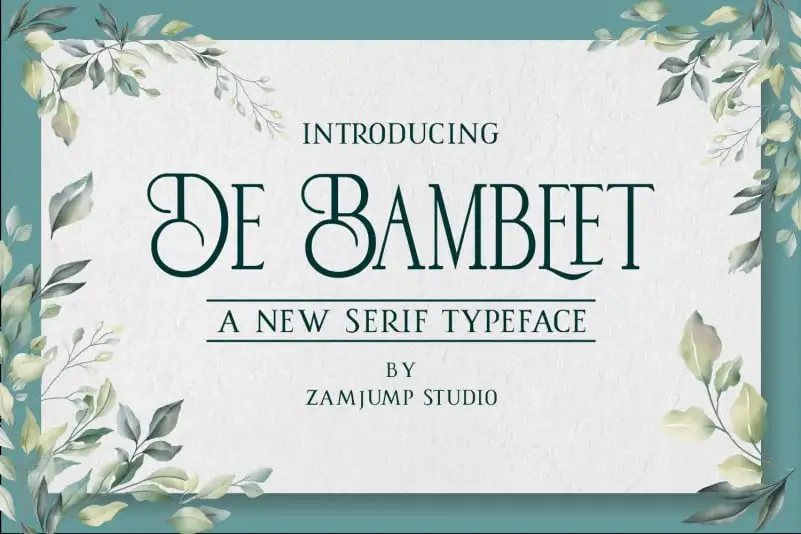
De Bambeet Serif Font – Fonte Grátis
De Bambeet Serif Font
A De Bambeet Serif é uma nova adição à família de fonts serif que combina modernidade com estilo único. Desenvolvida por zamjump através do site 99designs, essa fonte representa um equilíbrio elegante entre seriedade e personalidade, diferenciando-se dos outros tipos serifados tradicionais. Com múltiplas línguas, alternativas de letras e ligaturas intrigantes, ela se destaca como uma opção versátil para diversas mídias. Suas aplicações variam desde cartazes e convites de casamento até capas de livros, produtos em têxteis, arte fotográfica e embalagens de produto. A De Bambeet Serif é perfeita para designers que buscam uma fonte que seja tanto funcional quanto divertida, oferecendo a liberdade de explorar diferentes estilos em seus projetos.